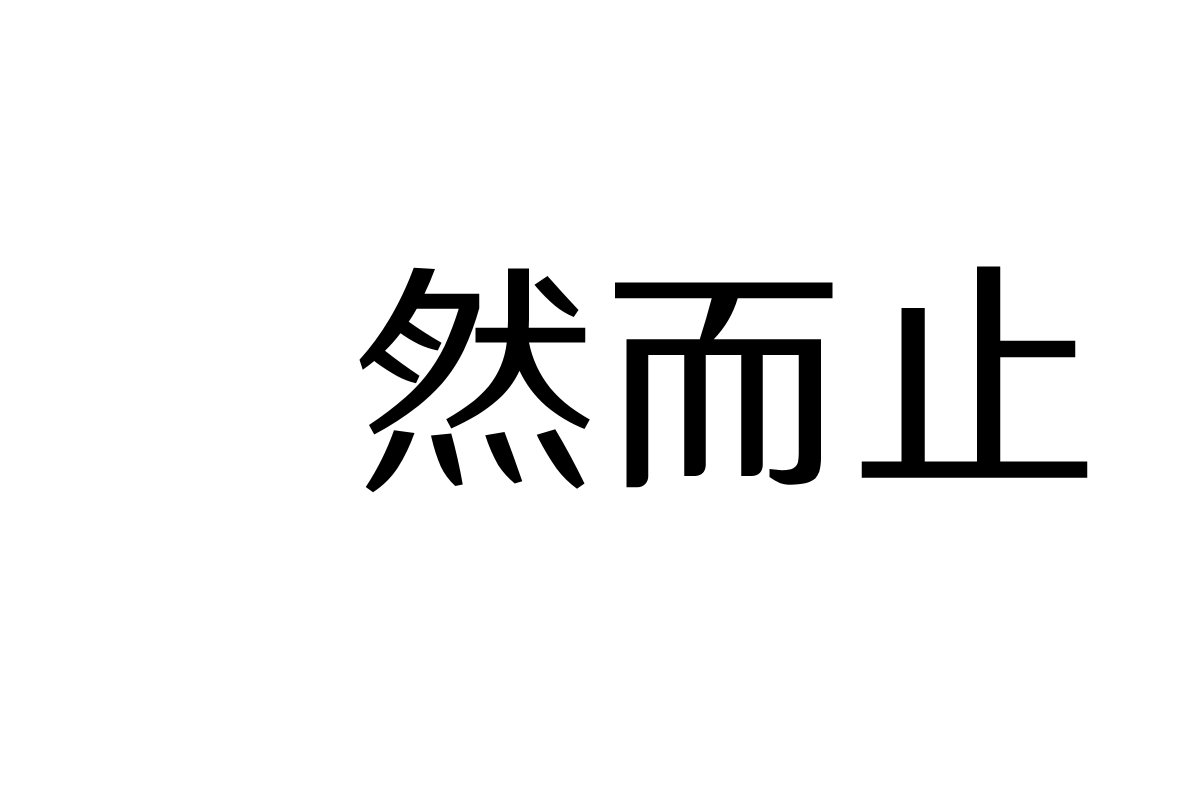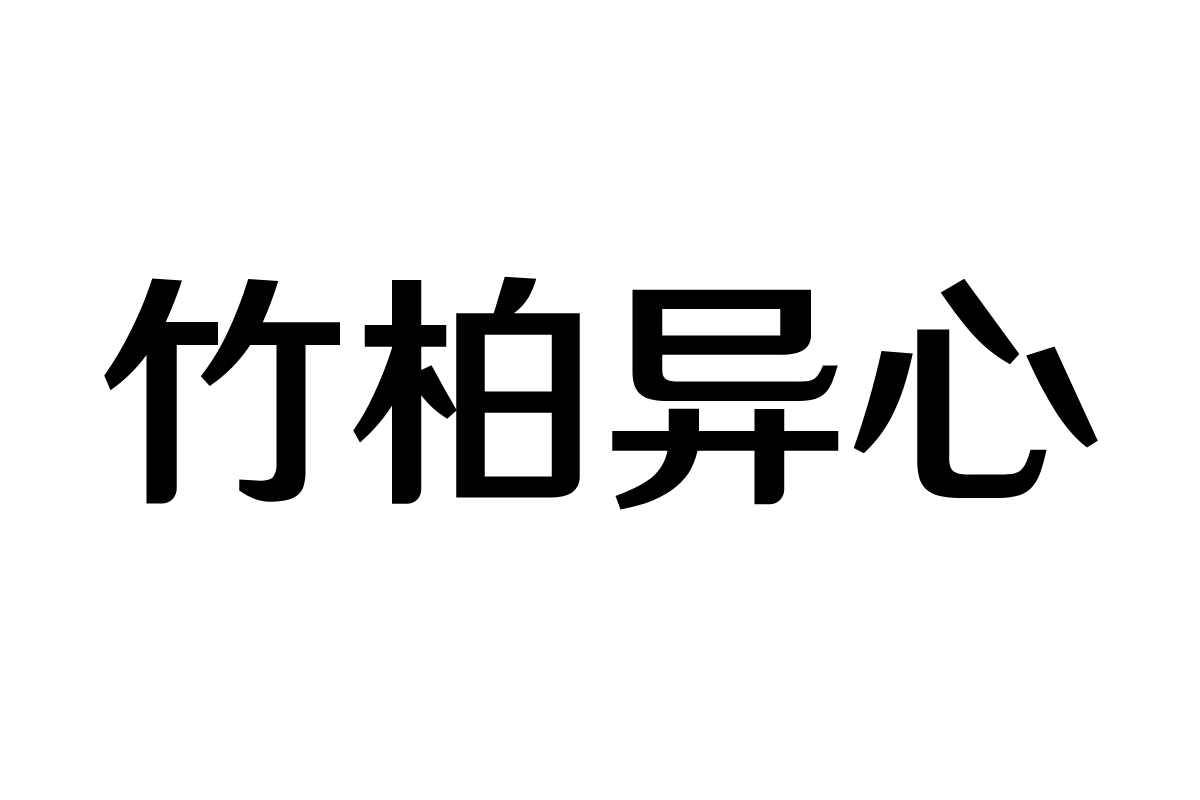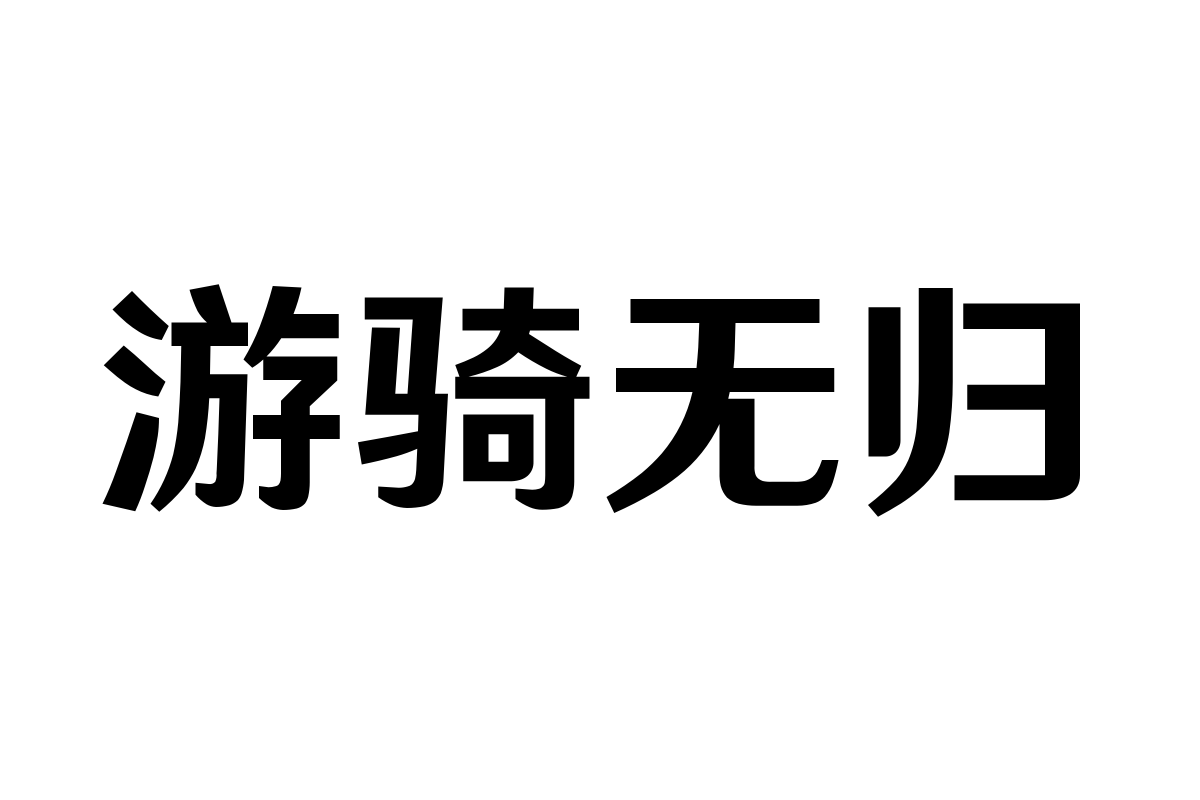
汉仪文黑-85是一款具有现代感的中文字体,由汉仪字库出品。这款字体的设计灵感来源于传统的书法艺术,同时又融入了现代审美元素,使得整体风格既典雅又时尚。
字体特点:
1. 字形结构:汉仪文黑-85采用了简洁明了的字形结构,线条流畅自然,给人一种轻松愉悦的感觉。
2. 笔画粗细:这款字体的笔画粗细适中,既不过于纤细,也不过于粗壮,适合用于各种文字设计需求。
3. 字体风格:汉仪文黑-85融合了传统书法与现代设计的元素,既有古典韵味,又不失现代感。
4. 适用范围:这款字体适用于各种文字设计场景,如标题、正文、广告、报纸等。
总之,汉仪文黑-85是一款兼具古典韵味与现代感的中文字体,适用于多种文字设计需求。